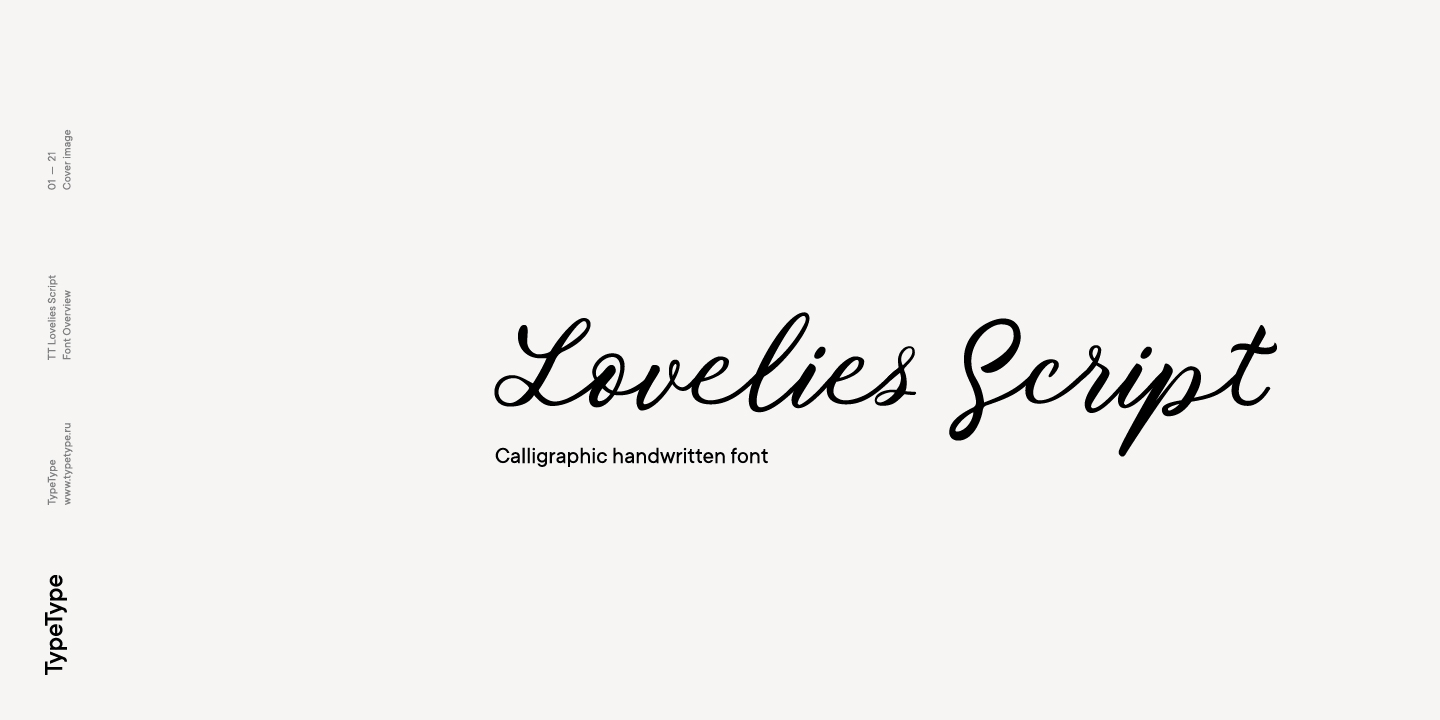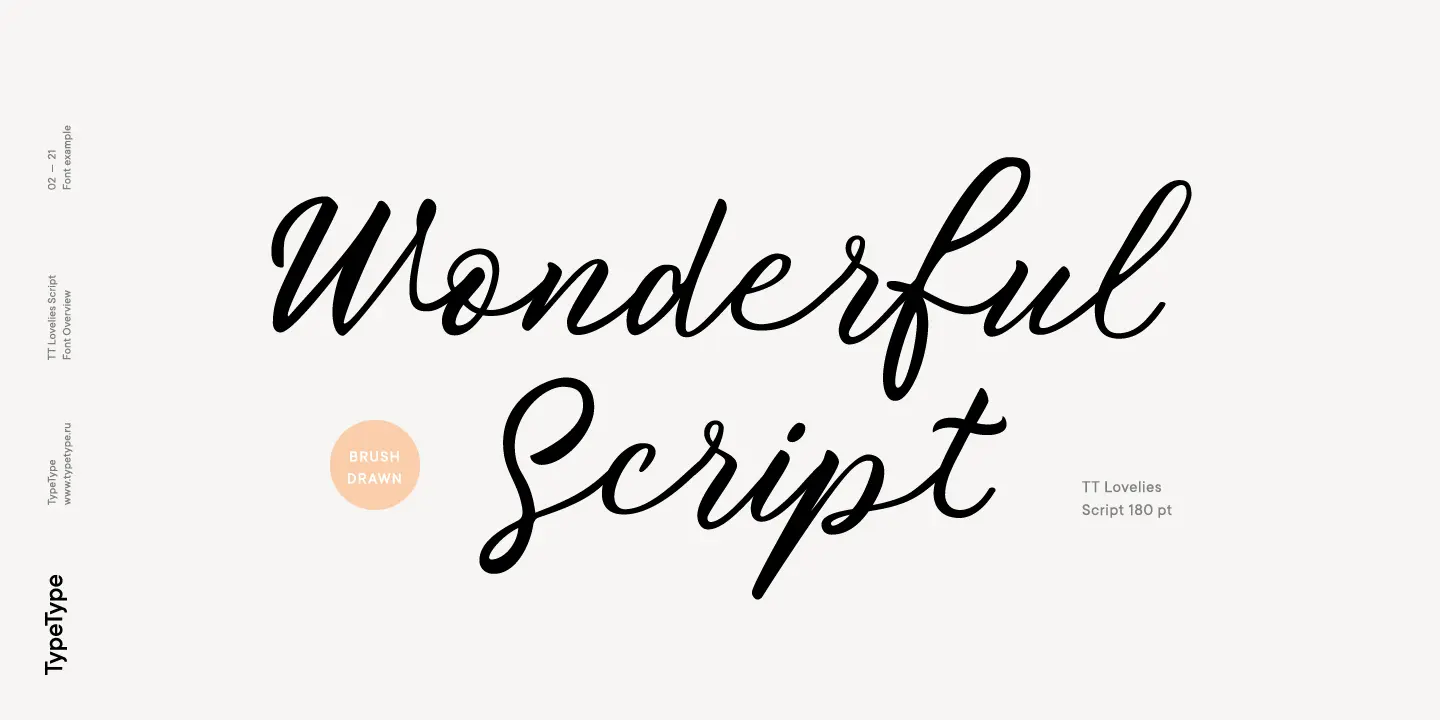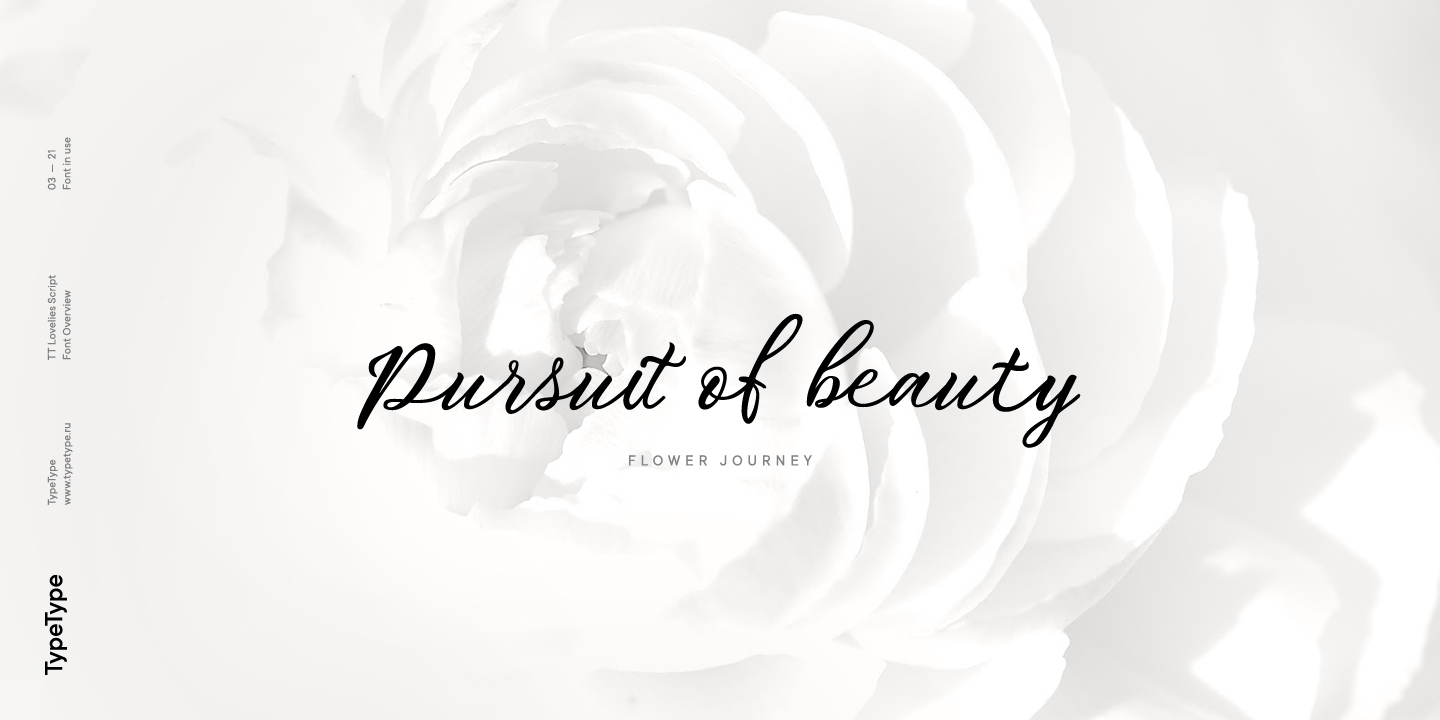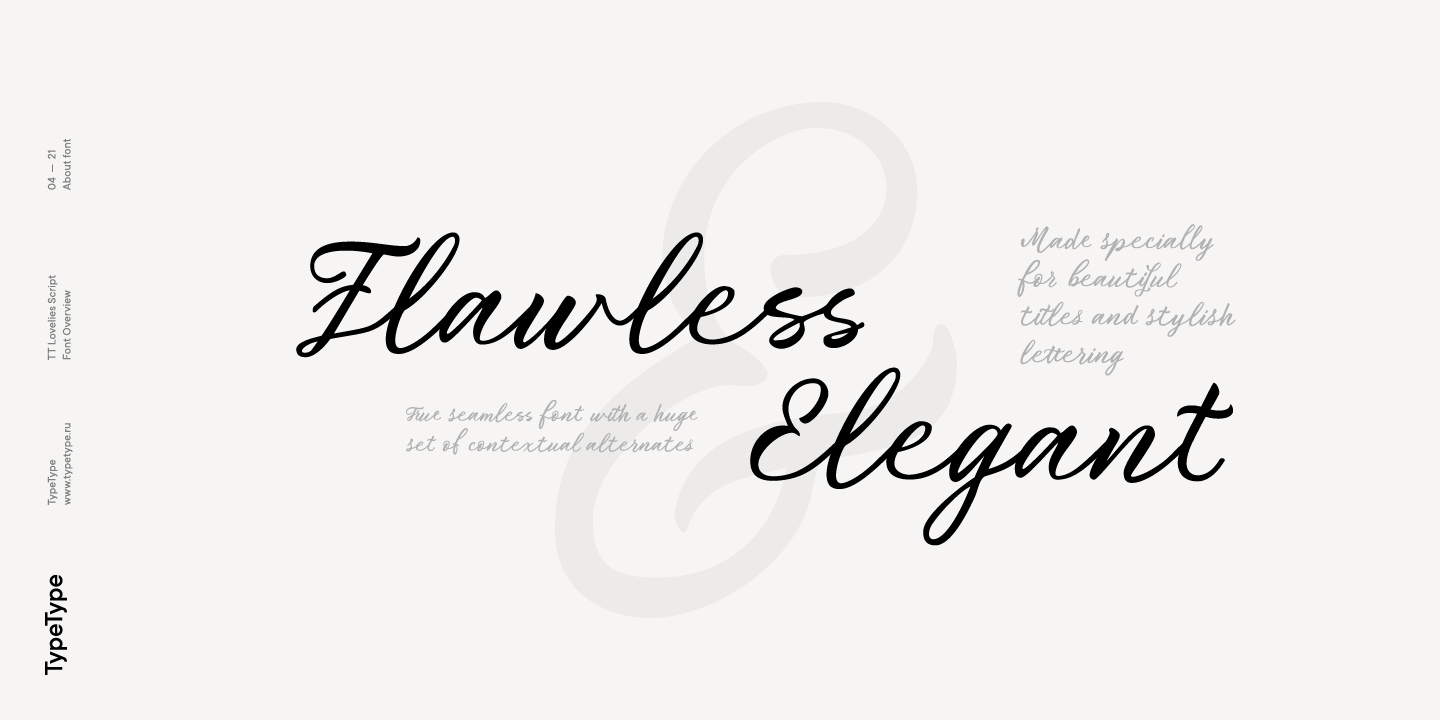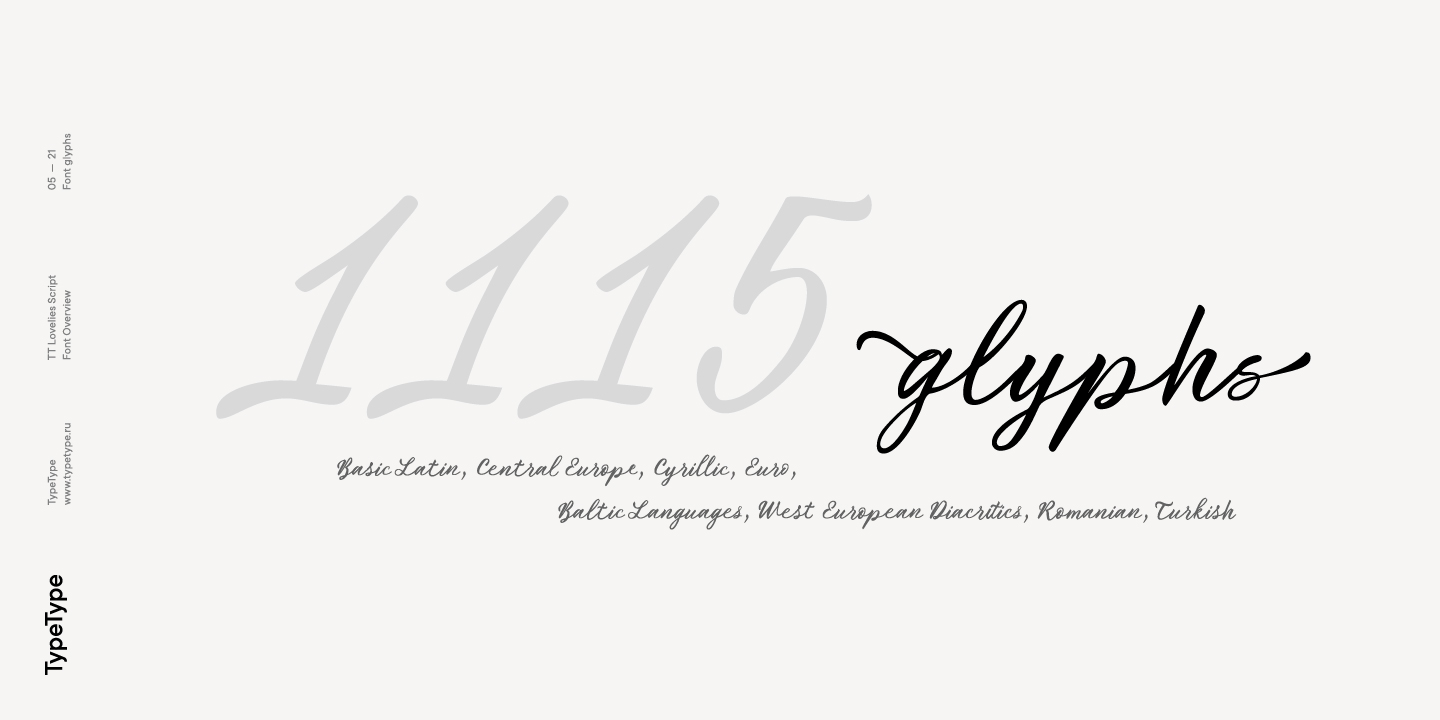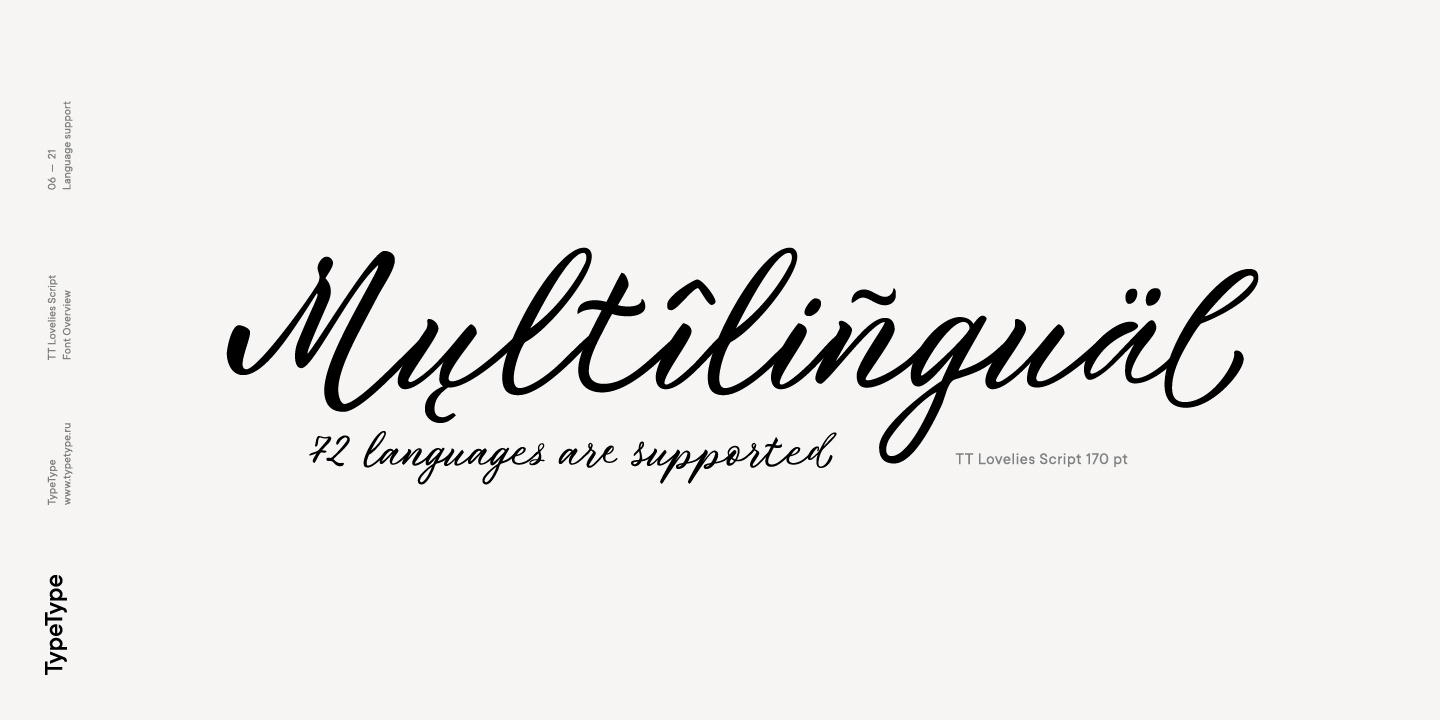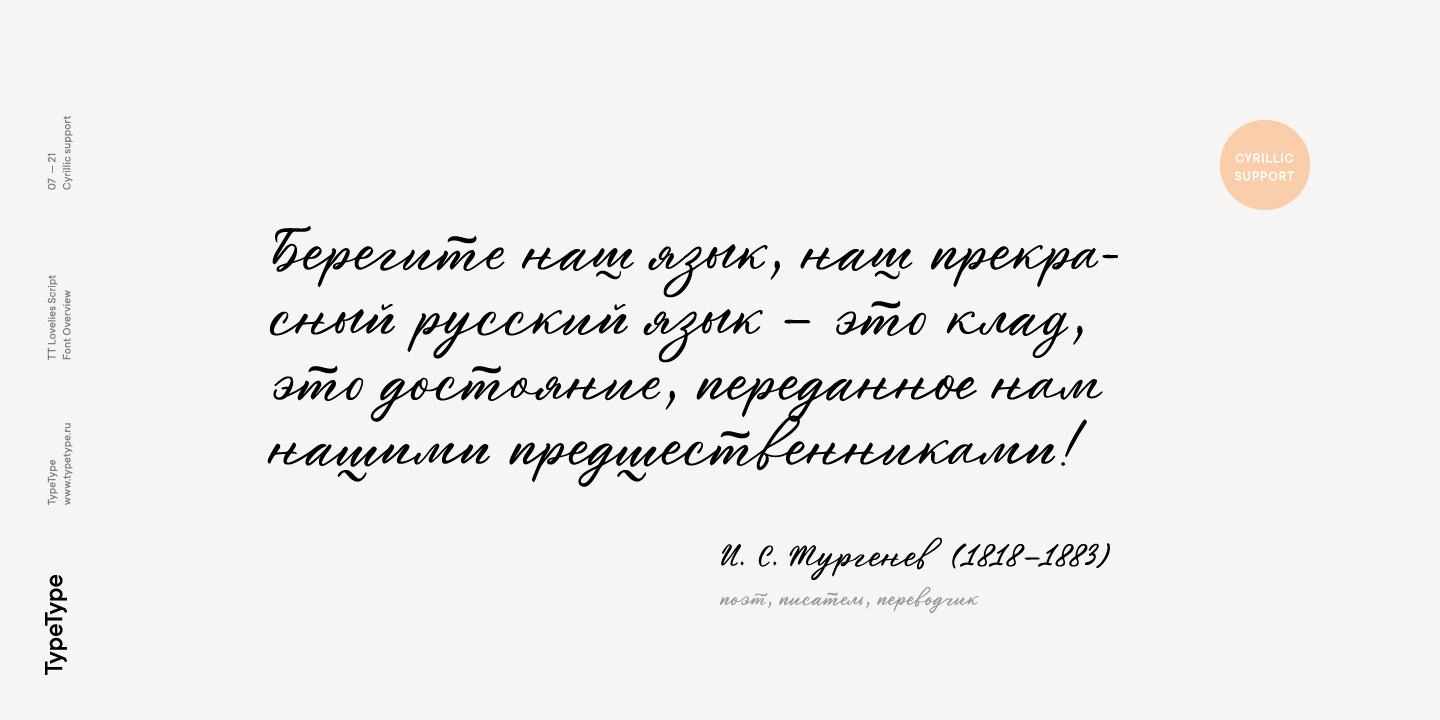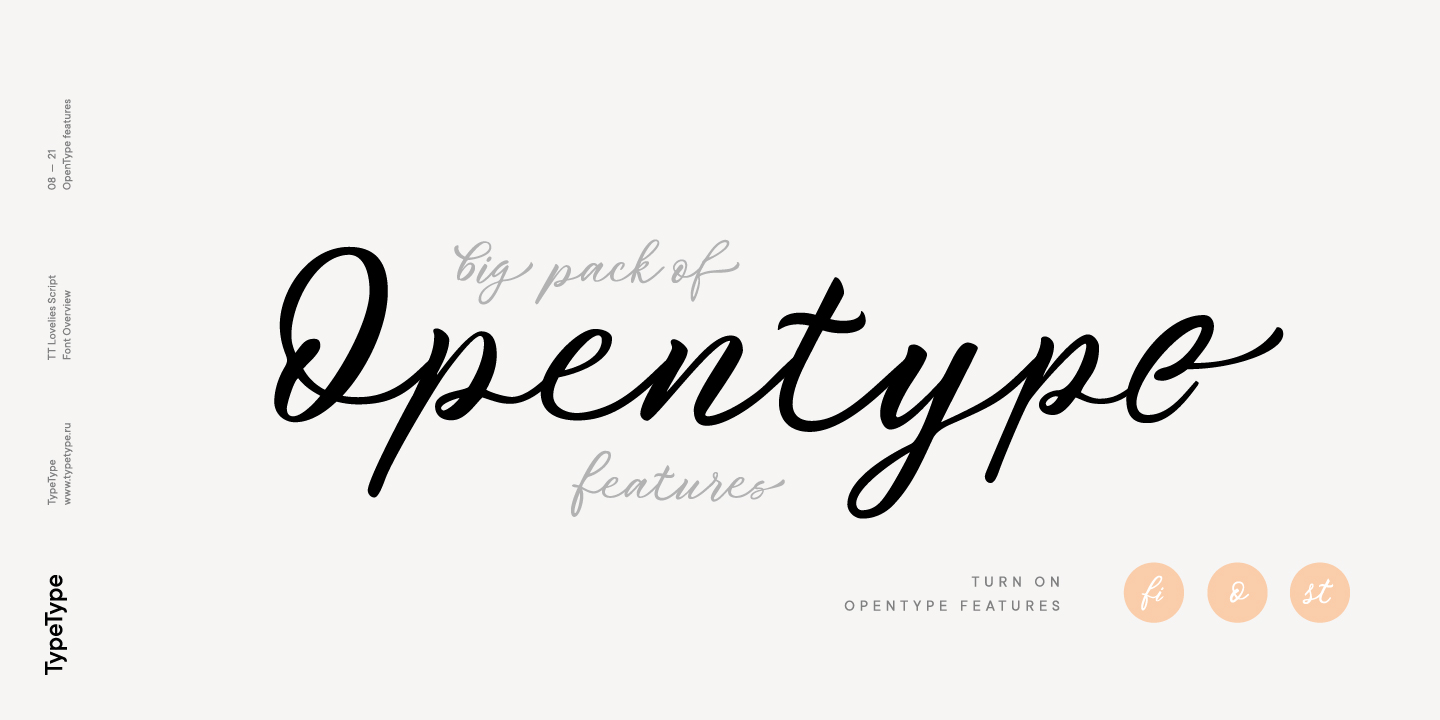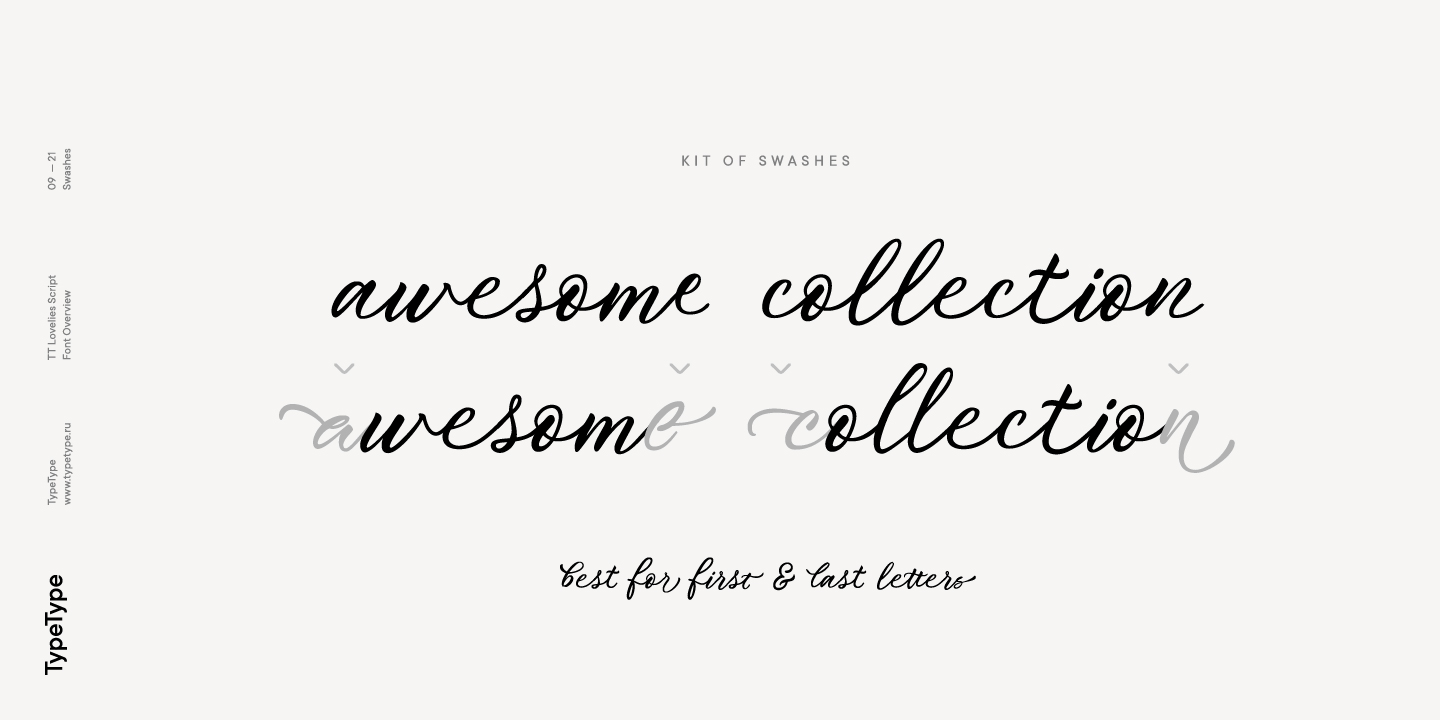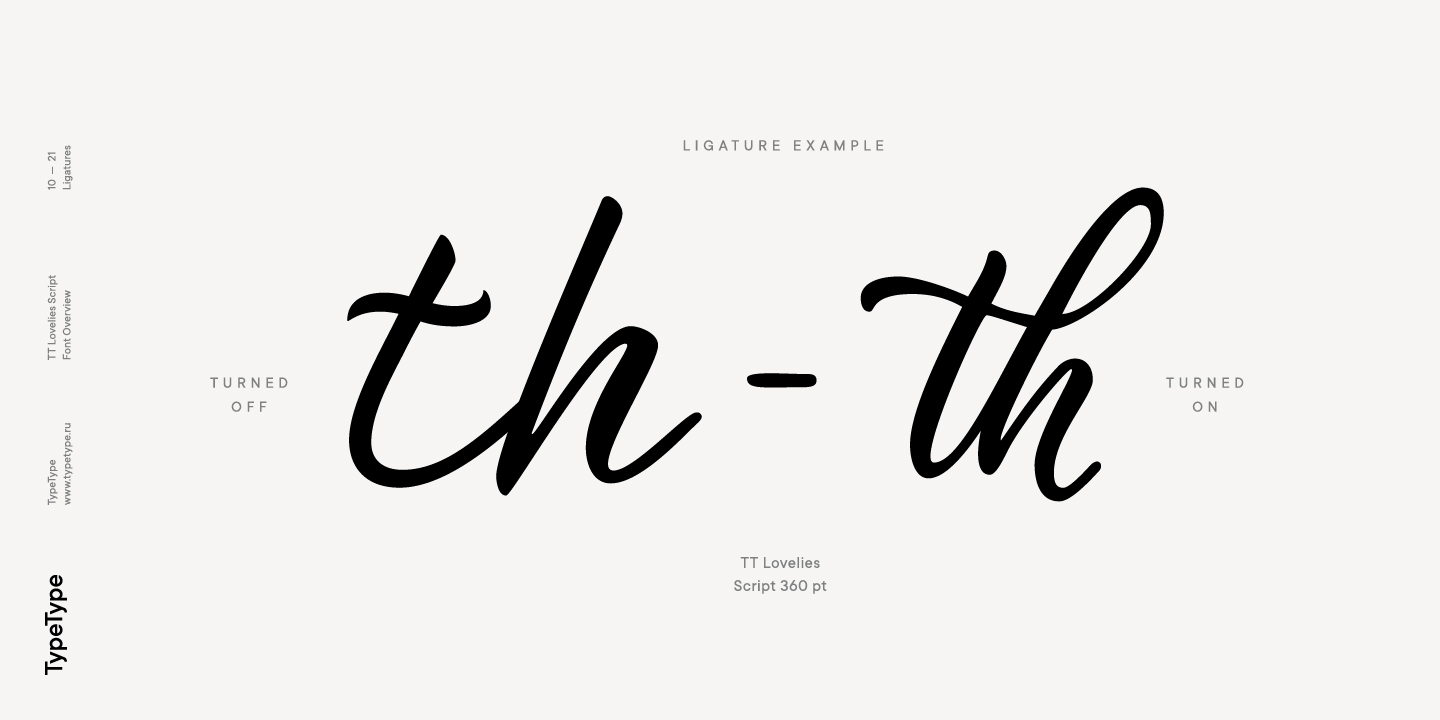
TT Lovelies Script
TT Lovelies Script — خط الكتابة اليدوية يتميّز برسوم متصلة وفريدة من نوعها، مستوحاة من الخط الكاليغرافي اليدوي الأصلي.
حول عائلة الخط TT Lovelies Script
TT Lovelies Script هو واحد من أكثر المشاريع تعقيدًا التي قمنا بها على الإطلاق. يحتوي على 1115 رمزًا، وأكثر من 2000 بديل سياقي، و10,000 زوج من التباعد بين الحروف، بالإضافة إلى عدد كبير من ميزات OpenType، بما في ذلك الزيادات والرقم الصغيرة. الميزة الرئيسية لهذا الخط هي استمراريته الحقيقية.
لقد أنجزنا ما كان يعتبر مستحيلًا: في TT Lovelies Script، حتى الأحرف الكبيرة تتصل بالأحرف الصغيرة في جميع الحالات بدون انقطاع. يعتمد الخط على خط اليد الذي صممه المصممة الروسية أليونا كوروبانوفا، والذي تحول من خط جميل إلى خط كامل الوظائف بفضل العمل الدؤوب. TT Lovelies Script هو خط حيوي ومرح مع بعض التفاصيل غير المتوقعة.
قم بتفعيل ميزات OpenType CALT وDLIG في برنامج التصميم الخاص بك لاستخدام الخط بكامل إمكانياته. تحتوي كل حرف صغير على زخارف مميزة تبدأ وتنتهي الكلمة. يتم تفعيل الزخارف تلقائيًا عند كتابة شرطيْن في بداية ونهاية الكلمات على التوالي. على سبيل المثال، اكتب — — apricot — — وستحصل على زخارف جميلة في بداية ونهاية الكلمة.
يستخدم TT Lovelies Script عددًا كبيرًا من البدائل السياقية والزيادات التي تساعد في الحفاظ على الإحساس بالخط اليدوي. لكل حرف رسم مخصص لنهاية السطر، ولتسهيل العمل مع الأحرف الكبيرة، قمنا بتضمين ميزة CaseSensitive في OpenType. أيضًا، للتعامل مع الأرقام، قمنا بتضمين: onum، sups، sinf، numr، dnom، frac، ordn. للاستفادة من جميع هذه الخيارات الرائعة، يجب عليك استخدام برامج تدعم ميزات OpenType.
liga | Standard Ligatures
fi
onum | Oldstyle Figures
1638
case | Case Sensitive Forms
({[H]})
frac | Fractions
1/2 3/4